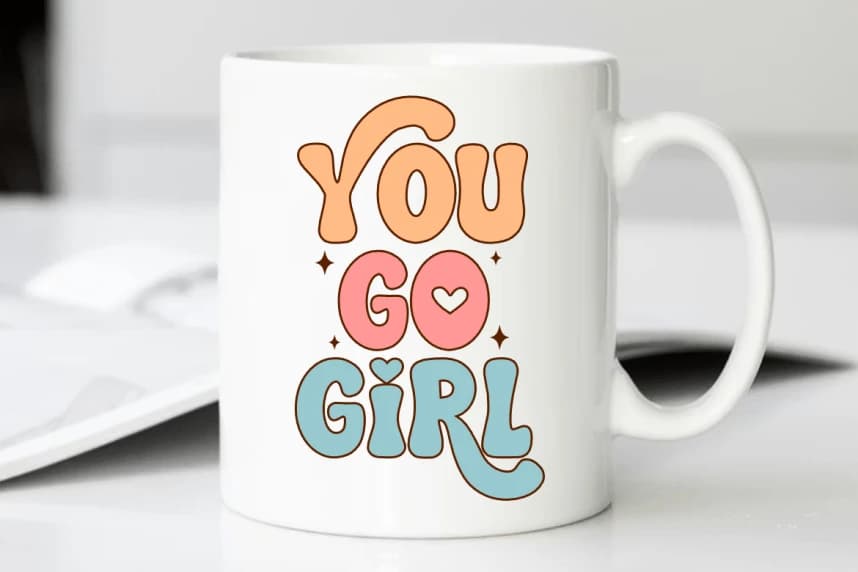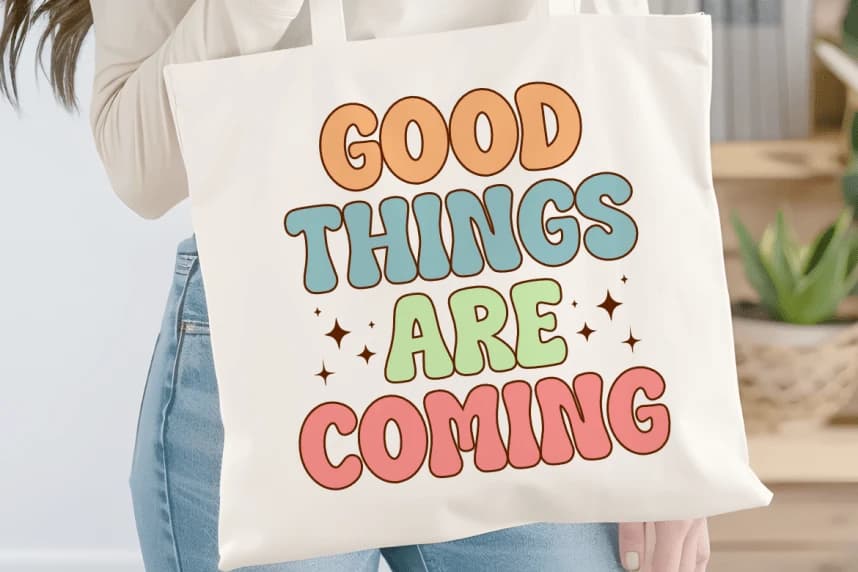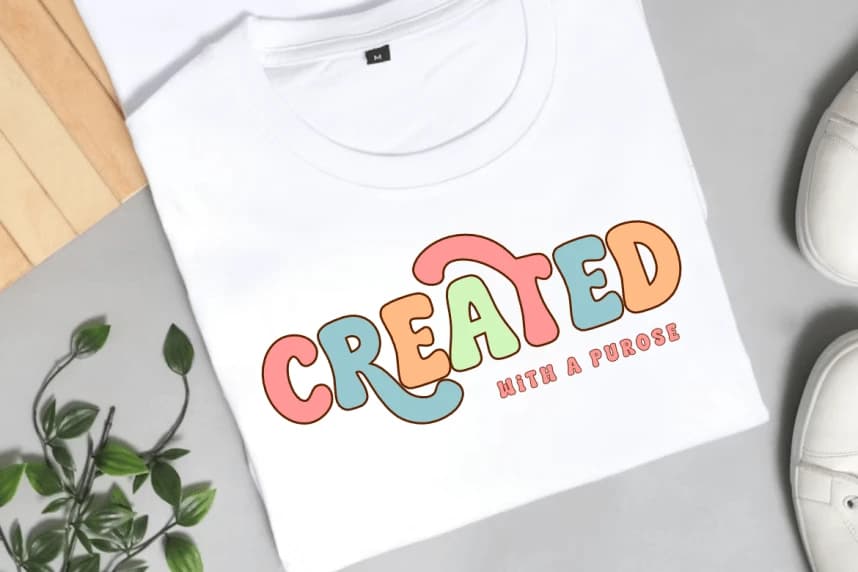
School Summer Font
School Summer Font, retro groovy bir gösterim yazı tipidir ve 70'lerin nostaljik havasını neşeli, modern bir dokunuşla mükemmel biçimde yakalar. Kalın, kabarcıklı çizgilere sahip olup tasarımın içine entegre edilmiş sevimli bir kalp vurgu öğesi içerir.
School Summer Font, 70'lerin nostaljik havasını neşeli, modern bir dokunuşla mükemmel bir şekilde yakalayan retro groovy bir display fontudur. Tasarımda entegre edilmiş kalın, kabarcıklı hatlar ve sevimli bir kalp vurgu içerir.